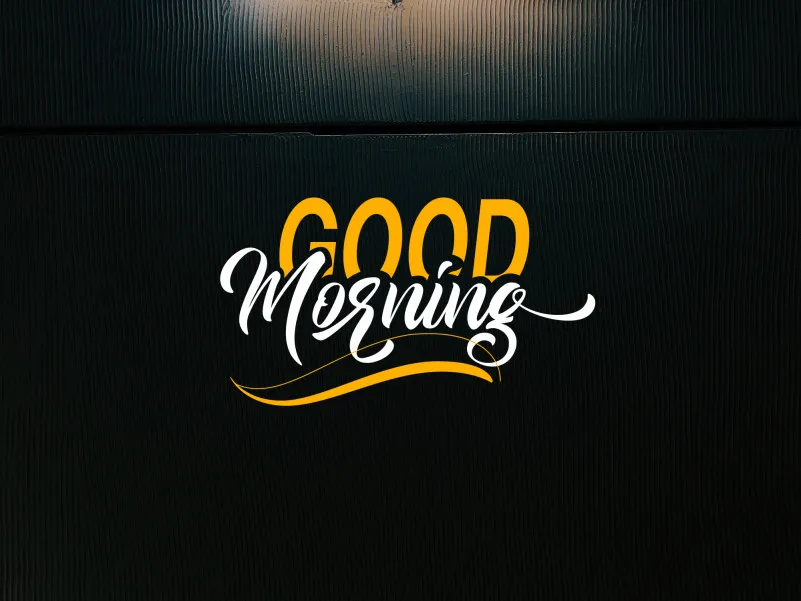
A Good Morning Script Font é uma elegante e charmosa tipografia cursiva que irá dar um toque especial a qualquer design que você criar. Inspirada no estilo delicado das cartas de amor, essa fonte adicionalmente suave vai deixar seu trabalho de design mais atraente e animado para os seus consumidores. Ideal para aqueles momentos especiais ou o amanhecer da sua criação visual, é perfeita para destacar mensagens de boas vindas com um toque delicado e encantador. Com um designer talentoso chamado khaiuns, essa fonte oferece uma experiência única que vai deixá-lo ansioso por explorar seus infinitos recursos criativos.